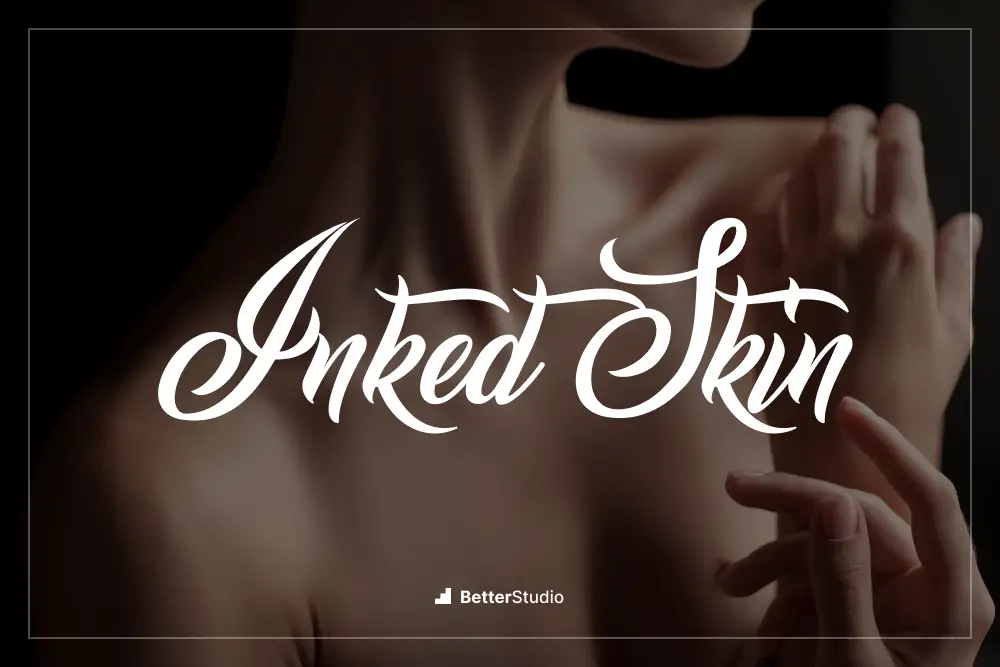
2023 年 21 种最佳 Figma 字体(免费和付费)
已发表: 2023-09-05您是一名平面设计师,正在寻找完美的字体来增强您的项目并将您的设计提升到一个新的水平吗? 别再犹豫了! 在这篇博文中,我们将探索 21 种最好的 Figma 字体,它们可以帮助您将创作转化为艺术作品。
如果您想知道为什么 Figma 字体具体如此,让我让您放心。 Figma 是全球数百万设计师使用的流行设计工具,以其直观的界面和强大的功能而闻名。
因此,无论您是经验丰富的专业人士还是刚刚起步,这些字体都一定会提升您的 Figma 设计。
现在,让我们深入了解文章本身。 我们根据流行度、多功能性和整体设计影响精心挑选了 21 种 Figma 字体。 每种字体都为表格带来了独特的东西,迎合不同的设计风格和目的。
无论您正在从事简约的品牌项目还是充满活力的编辑布局,此列表中的字体都能满足您的需求。
因此,事不宜迟,让我们探索 Figma 字体的世界,并了解这些排版宝石如何对您的设计项目产生重大影响。
最佳优质 Figma 字体
您是一名平面设计师,希望将您的项目提升到一个新的水平吗? 我们精选的最佳优质 Figma 字体系列就是您的最佳选择。 这些字体经过精心制作,可增强您的设计并使它们栩栩如生。
布瓦塔
Bouvata 是一种手工制作的显示字体,将为您的设计带来独特的个性化风格。 其手绘风格增添了温暖和个性,使其成为各种项目的理想选择,包括贺卡和徽标。
借助 Bouvata,您可以为您的设计添加个人风格,使其脱颖而出并吸引观众的注意力。 无论您是要创建衷心的贺卡还是专业的徽标,这种字体都会增添额外的魅力和真实性。
Bouvata 的突出特点之一是其手工制作的品质。 该字体具有自然、有机的感觉,仿佛是用爱和关怀手工创造的。 这为您的设计增添了温暖和个性的感觉,使它们感觉更加人性化和相关。
奥滕
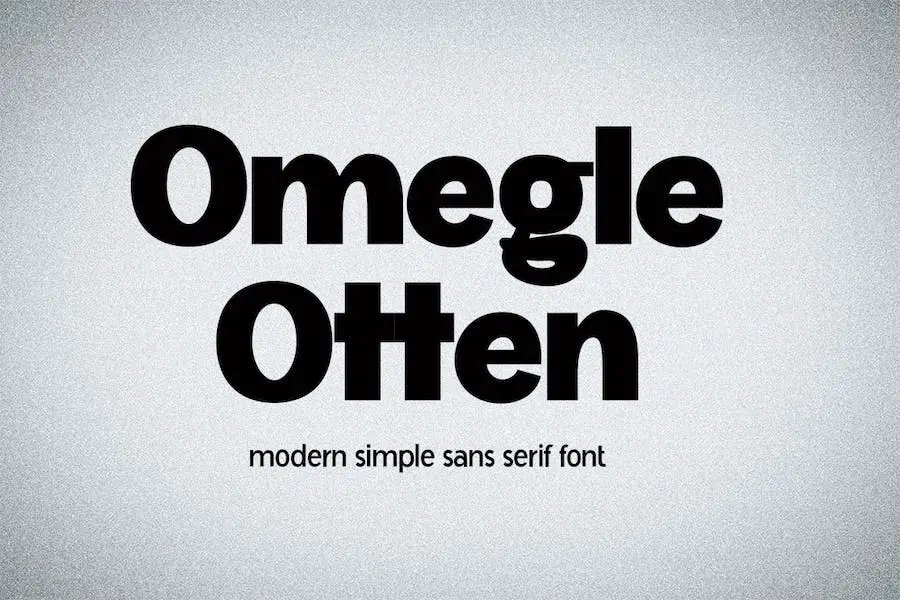
Omegle Otten 是一款时尚优雅的无衬线字体,可为任何设计项目增添现代感。 凭借其易于使用的功能,它是各种设计项目的完美字体选择,让您能够创建视觉上令人惊叹的专业设计。
Omegle Otten 干净简约的设计使其用途广泛,适合各种项目。
无论您是设计徽标、创建网站还是开展品牌项目,这种字体都将增强整体美感,并为您的设计带来精致和现代的外观。
Omegle Otten 的主要优势之一是其易用性。 该字体设计为用户友好型,让您可以轻松地将其融入您的设计中。
凭借其流畅的线条和平衡的比例,它创造出和谐且具有视觉吸引力的构图,使您的设计脱颖而出。
卢德科
Ludeco 是一种现代显示字体,为经典装饰艺术风格增添了独特的风格。 其不对称结构和精心设计的重量转移创造出令人惊叹和引人注目的图案。
这种字体非常适合希望为其项目增添一丝优雅和精致的图形设计师。
Ludeco 独特的字体散发着创造力和个性感。 凭借其不对称结构,这种字体在人群中脱颖而出,立即吸引人们的注意。
每个字母形状中独特的重量变化创造了一种视觉上迷人的图案,为任何设计增添了深度和个性。
无论您是在制作徽标、海报还是网站,Ludeco 的现代魅力都会将您的项目提升到一个新的水平。 其经典装饰艺术风格与当代设计元素的结合使其成为各种应用的多功能选择。
巴伦坎卡
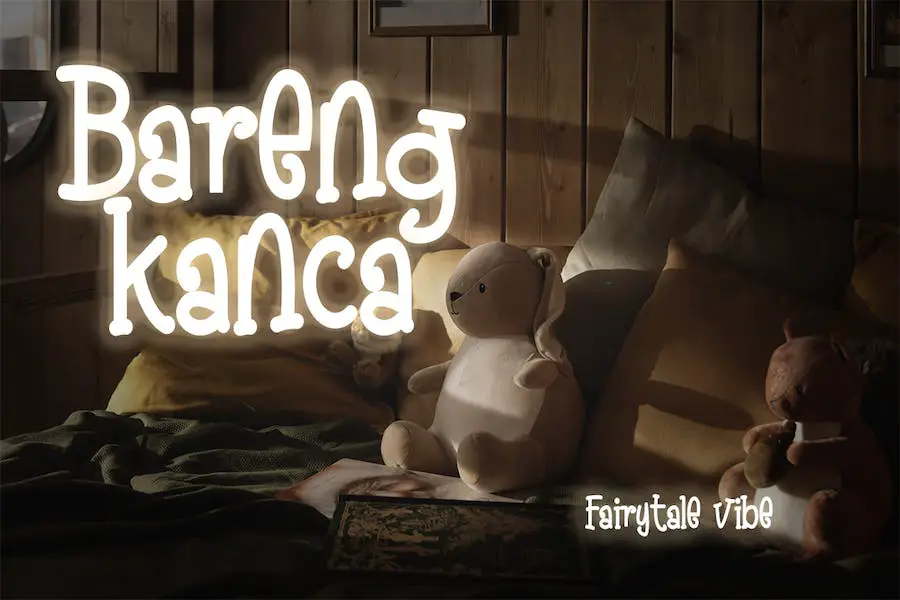
Bareng Kanca 是一种美丽而异想天开的字体,为您的设计带来一丝魔力。 这种字体具有童话般的氛围,非常适合为您的项目添加迷人的元素。
无论您是设计书籍封面、为社交媒体创建图形,还是从事品牌项目,Bareng Kanca 都会将您的设计提升到一个全新的水平。
Bareng Kanca 的突出特点之一是其独特且引人注目的美学。 该字体具有俏皮和梦幻的品质,一定会吸引您的观众。
其复杂的细节和优美的曲线营造出优雅和魅力的感觉,使其成为各种设计目的的多功能选择。
Bareng Kanca 不仅具有视觉吸引力,而且也非常易读。 该字体精心设计的字形确保您的文本清晰易读,即使尺寸较小。
这使得它成为设计中正文、标题或任何其他文本密集元素的实用选择。
穆恩克拉尔
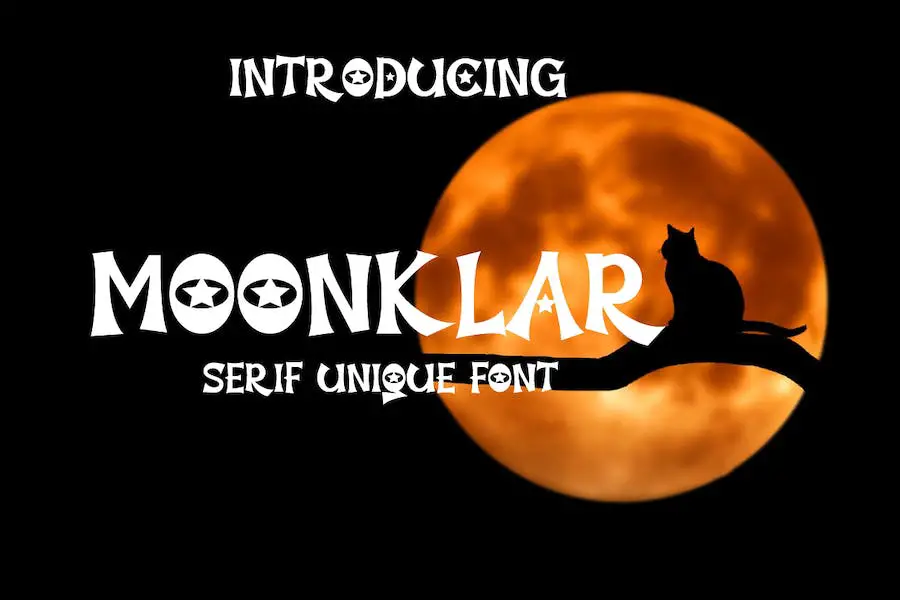
Moonklar 是一种迷人的装饰性显示字体,非常适合各种设计项目。 无论您是在创建徽标、杂志、社交媒体图形、小册子还是任何其他视觉内容,这种字体都会增添一丝独特性和风格。
其复杂的装饰元素使其脱颖而出,让您能够创造出视觉上令人惊叹的设计,给您的观众留下深刻的印象。
借助 Moonklar,您可以轻松提升设计的外观和感觉。 其独特而引人注目的功能使其成为那些想要创建视觉上令人惊叹和令人难忘的图形的人的理想选择。
该字体复杂的细节和装饰元素为您的设计增添了深度和特色,使其真正成为独一无二的。
Moonklar 最好的事情之一就是它的多功能性。 它可以轻松地融入到各种设计项目中,从徽标到小册子再到社交媒体图形。
其装饰性使其可用于网页和印刷设计,确保您的创造力无极限。
独白
Monologue 是一种简单而独特的显示字体,非常适合寻找字体来增强项目设计的图形设计师。 它是标志设计、杂志布局、社交媒体图形、宣传册和许多其他创意应用的理想选择。
通过 Monologue,设计师可以使用一种为他们的作品增添个性和风格的字体。 其简洁的线条和鲜明的个性使其引人注目且用途广泛。
无论您是制作专业徽标还是创建引人入胜的社交媒体内容,这款字体都能满足您的需求。
《独白》的关键属性之一是它的多功能性。 它可用于广泛的设计项目,使设计师能够在不同媒介上保持一致性和有凝聚力的视觉识别。
它与各种设计元素无缝融合,使其适应不同的风格和审美。
单色
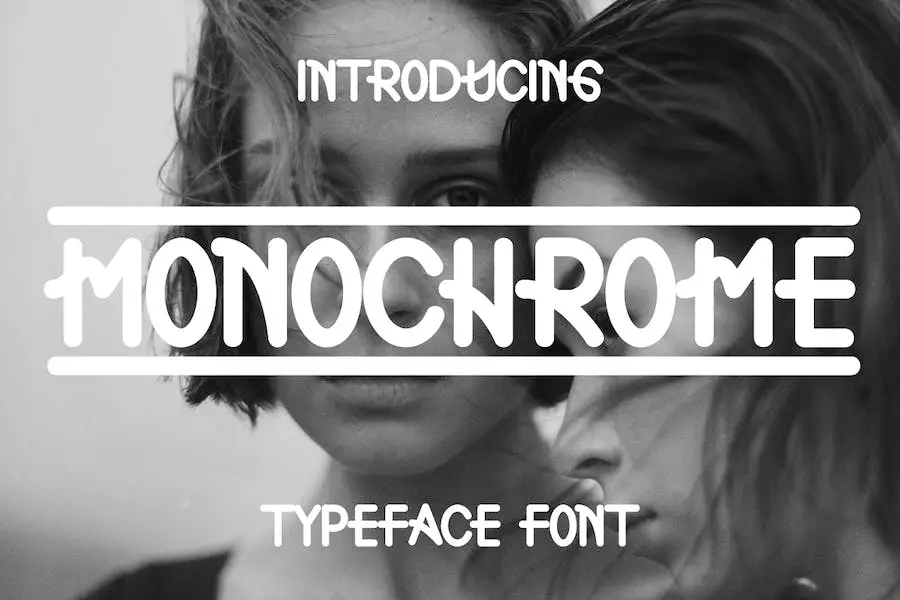
单色是一种独特的显示字体,非常适合徽标设计、杂志、社交媒体、宣传册等。 它的多功能性使其成为寻求增强项目设计的图形设计师的绝佳选择。
使用 Monochrome,您可以为您的设计增添一丝优雅和精致。 无论您是在制作专业徽标还是创建引人注目的社交媒体图形,这种字体都将帮助您从人群中脱颖而出。
Monochrome 的突出特点之一是其现代时尚的设计。 每个字母简洁的线条和圆滑的曲线营造出一种视觉上吸引人的美感,一定会引起人们的注意。 对于那些想要为自己的设计增添现代感的人来说,它是完美的选择。
上帝保佑
Godbless 是一种现代而简单的显示字体,非常适合徽标设计、杂志布局、社交媒体帖子、小册子等。 它提供了干净、时尚的美感,将提升您正在从事的任何项目的设计。
该字体专为增强您的创造力并为您的设计赋予专业和精美的外观而设计。
凭借其简洁的线条和多功能的风格,它可以用于各种设计目的,无论您是为品牌创建徽标还是为杂志设计布局。
Godbless 的突出特点之一就是它的简单性。 该字体赏心悦目,具有简约的感觉,适合多种设计风格。
无论您想要时尚现代的外观还是干净简约的设计,这种字体都可以满足您的需求。
朗基
Runkey 是一种怪异且复古的黑体字体,非常适合徽标设计、杂志、社交媒体、宣传册等。 凭借其独特而怪异的风格,它为任何设计项目增添了一种令人难以忘怀的感觉。
无论您是想创建一个独特的徽标,还是需要一种能够捕捉旧世界魅力精髓的字体,Runkey 都是完美的选择。
Runkey 的怪异和复古美学使其成为恐怖主题设计、哥特文学项目甚至万圣节主题促销的绝佳选择。
其黑体设计向传统排版致敬,为您的作品增添神秘和精致的气息。 无论什么项目,Runkey 都一定会吸引并吸引您的受众。
Runkey 的多功能性确实令人惊叹。 无论您是为鬼屋设计徽标还是以文学作品为特色的杂志传播,这种字体都可以轻松适应任何环境。
其清晰明快的线条确保了易读性,而独特的字母形状则增添了个性和吸引力。
六角体
Hexsome 是一种简单而独特的字体,非常适合徽标、杂志、社交媒体帖子、宣传册等设计项目。 它提供干净、现代的外观,将增强您的整体设计。
凭借其多功能性,您可以在各种应用程序中使用 Hexsome 来创建具有视觉吸引力和专业外观的设计。 无论您是从事客户项目的图形设计师还是希望改进个人设计的个人,Hexsome 都是您需要考虑的字体。
它将为您的作品增添额外的优雅和风格,使其在人群中脱颖而出。 那么,当您可以使用 Hexsome 来提升您的设计项目时,为什么还要选择普通字体呢?
尝试一下,看看它将您的设计变成非凡的东西所带来的不同。
起义
Revolte 是一种现代衬线字体,是徽标设计、杂志布局、社交媒体帖子、小册子等的完美字体。 凭借其简洁时尚的设计,它为任何项目增添了一丝精致感。
它用途广泛,可用于各种设置,这使其成为任何图形设计师的宝贵资产。 无论您是在制作品牌材料还是为社交媒体创建引人注目的视觉效果,Revolte 都能满足您的需求。
其清晰的线条和独特的字体使其美观且易于阅读。 使用这种优雅且多功能的字体提升您的设计。
冲击波
Blaster 是一种简单的现代衬线字体,非常适合各种设计项目。 它非常适合创建令人惊叹的徽标、设计迷人的杂志、制作引人入胜的社交媒体帖子以及制作引人注目的小册子等用途。
Blaster 时尚而现代的设计使其成为图形设计师的多功能选择。 其简洁的线条和优雅的曲线为任何项目增添了一丝精致感。
无论您是想创建专业徽标还是设计引人注目的社交媒体帖子,Blaster 都是可以将您的设计提升到新水平的字体。
Blaster 的应用范围广泛,可以跨不同平台使用。 无论您是在进行徽标设计、杂志布局、社交媒体图形还是小册子,Blaster 都能确保您的排版准确无误。
Blaster 不限于特定行业或风格。 其永恒的吸引力使其能够无缝融入各种设计美学,从简约到大胆和现代。 这种多功能性确保您可以在任何设计项目中使用 Blaster,无论所需的风格或主题如何。
莫里克斯
Movericks 是一种时尚且多功能的衬线字体,非常适合增强您的创意项目。 该字体设计简洁优雅,非常适合徽标设计、杂志、社交媒体帖子、宣传册等。
它为您的设计提供简单而精致的触感,增添专业和时尚的外观。 无论您是在制作品牌材料还是设计引人入胜的社交媒体图形,Movericks 都一定会提升您的项目并使其脱颖而出。
其多功能性使其适合各种设计目的,为您的创意努力提供无限的可能性。 使用 Movericks 升级您的设计游戏,并以其永恒的魅力将您的愿景变为现实。
波尔图
Porto 是一种装饰性无衬线字体,非常适合各种设计项目。 无论您是在设计标志、杂志、社交媒体图形、小册子还是其他任何东西,波尔图都可以以其独特而时尚的美感提升您的作品。
凭借其干净、现代的外观,波尔图为任何设计增添了一丝精致。 其装饰元素使其从其他基本无衬线字体中脱颖而出,为您的项目带来独特且令人难忘的外观。
Porto 的多功能性使其成为各种设计目的的绝佳选择。 它可用于标题和正文,让您在整个设计中保持一致的外观。
该字体的灵活性意味着它可以适应不同的风格和主题,使其成为任何图形设计师工具包的宝贵补充。
最好的免费 Figma 字体
另一方面,糟糕的字体选择或糟糕的排版可能会使内容难以阅读,从而导致令人沮丧的用户体验。
使用最好的 Figma 字体可以增强设计的整体视觉吸引力,使其更具可读性和可访问性,并帮助您建立一致的视觉品牌。
字体还可以促进整体用户体验并传达正确的语气和信息,使它们成为设计的一个重要方面。
结论
总之,我们探索了 21 种最好的 Figma 字体,它们可以极大地增强您的项目设计。 从经典优雅的选择到现代引人注目的选择,这些字体提供了广泛的样式以适合任何项目。
无论您是图形设计师还是只是想改进您的设计,这些字体都绝对值得一看。